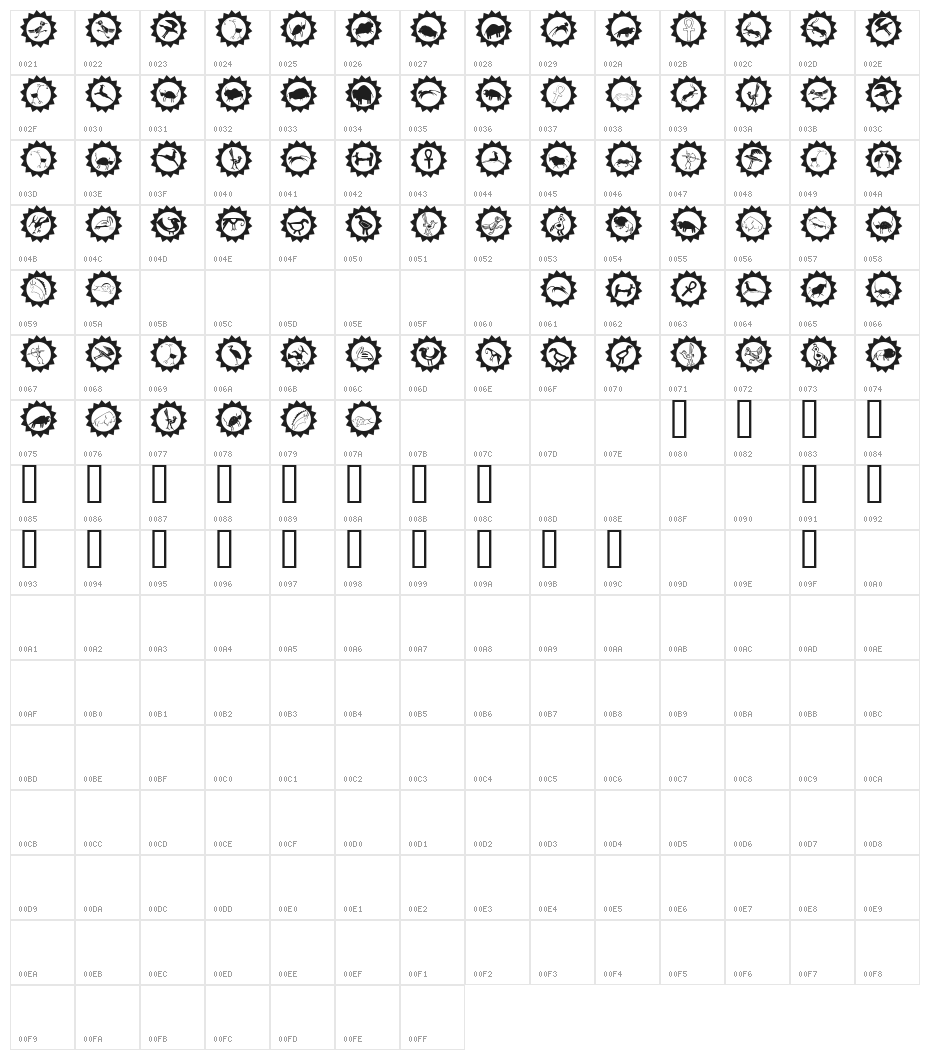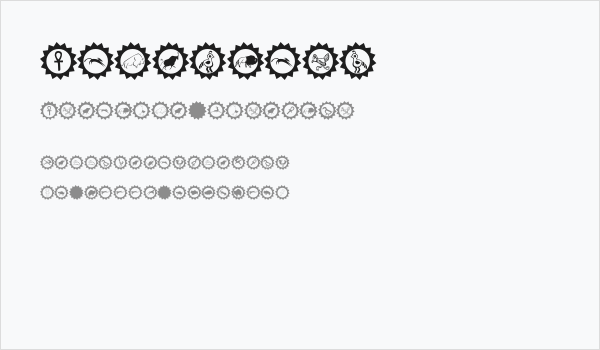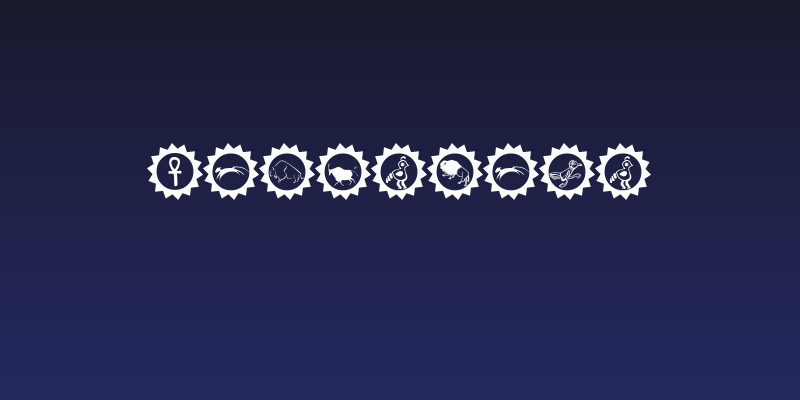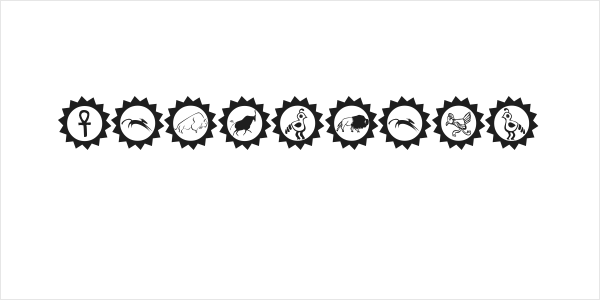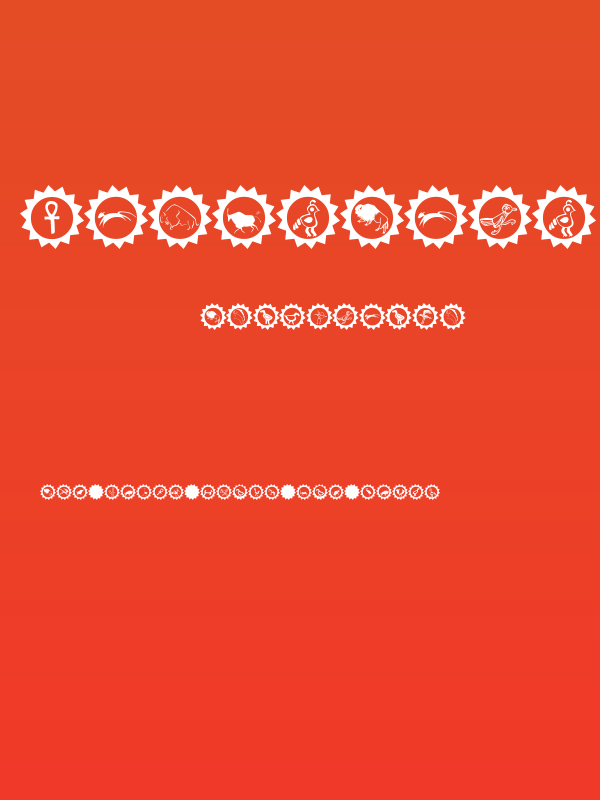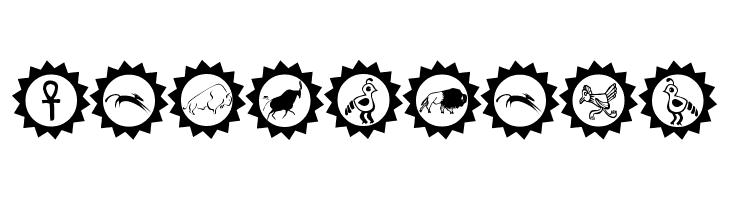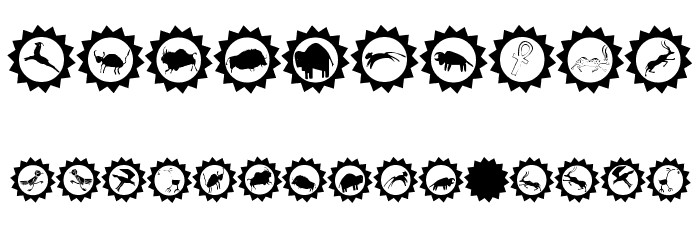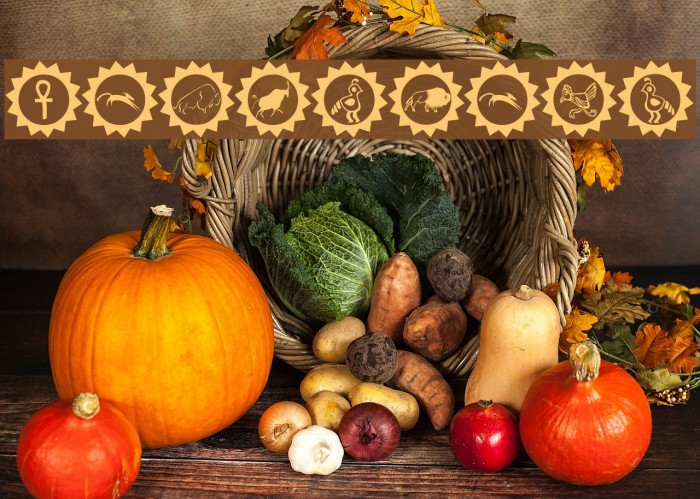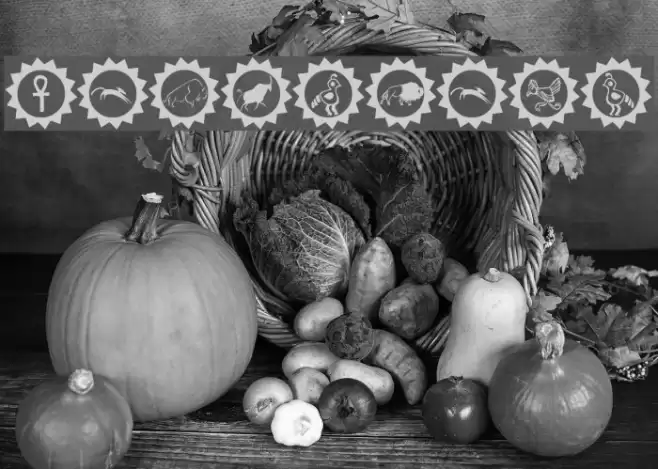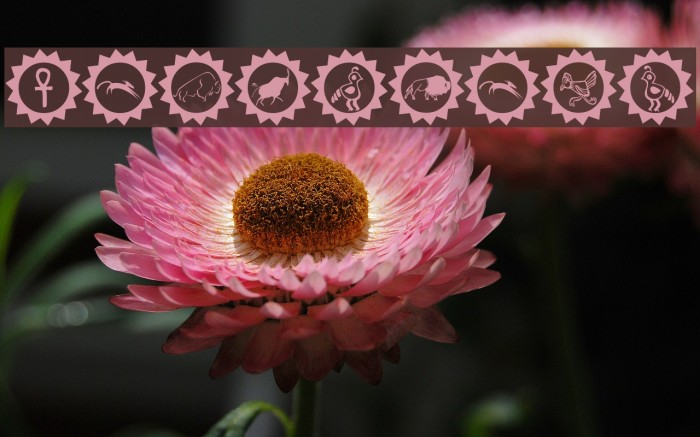
CaveStars Font
| Estilo geral | Decorative, Primitive, Playful |
| Caso de uso | Logos, Posters, Themed Headlines, Educational Materials |
| Projetos propostos | Children’s books, educational posters, themed party invitations, museum exhibits, prehistoric or adventure branding, creative crafts. |